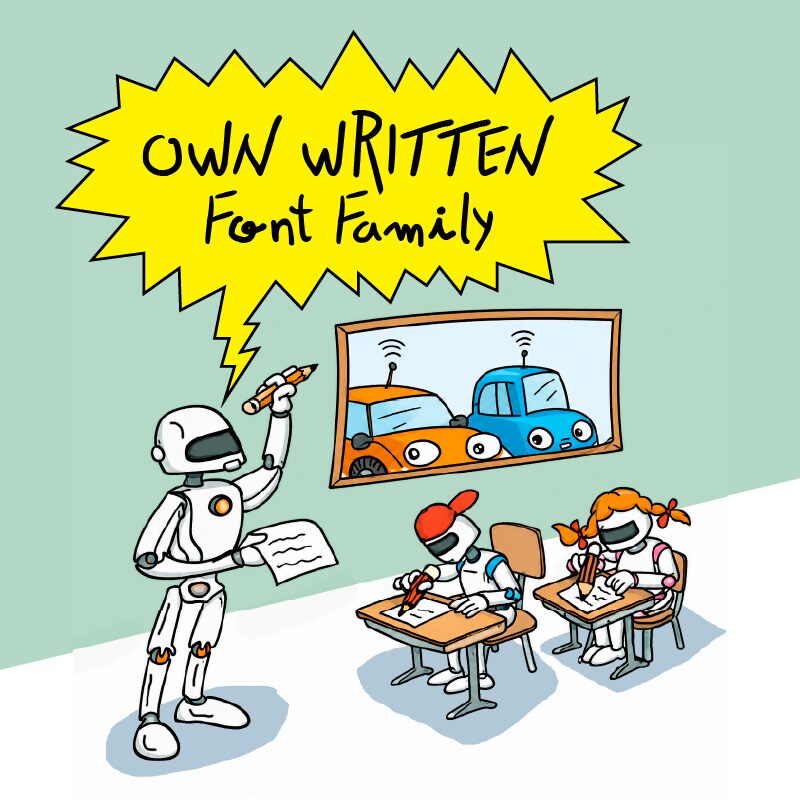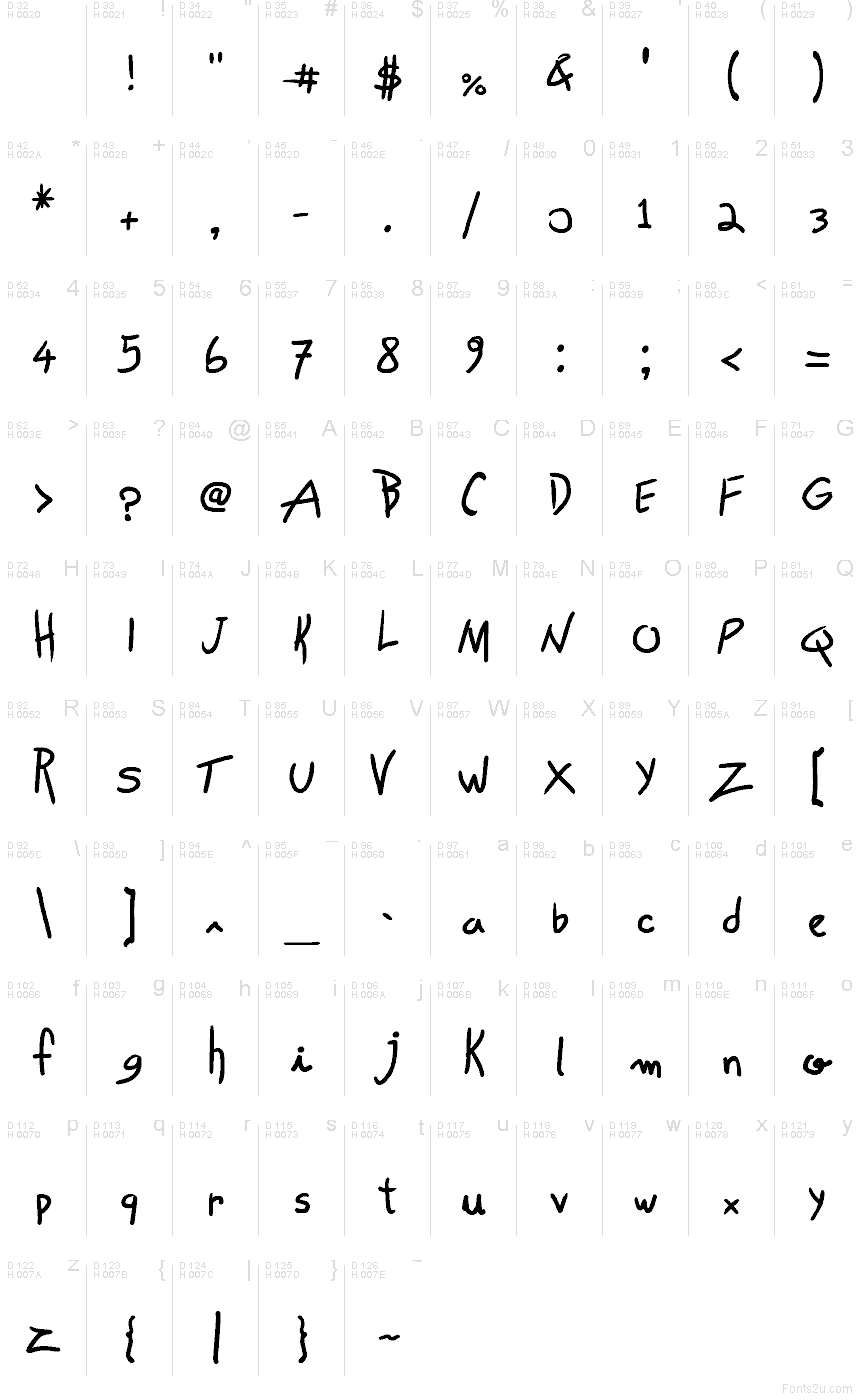
Own Written par Galdino Otten Fonts est une police manuscrite décontractée gratuite aux traits arrondis et au mouvement rapide et irrégulier d'une écriture au feutre. Ses liaisons souples et l'épaisseur changeante de ses traits confèrent à l'écriture un caractère personnel.
Les designers créant des projets conviviaux pour les familles ou les entreprises indépendantes peuvent l'utiliser pour des emballages pour enfants, l'identité visuelle de cafés et des affiches d'événements communautaires. Ses courbes douces conviennent aux produits dérivés ornés de mascottes dessinées à la main ou de simples gribouillages, où les lettres peuvent s'intégrer à l'illustration plutôt que de faire office d'étiquette formelle. Sa forme informelle se révèle particulièrement convaincante pour les thèmes culinaires ludiques, les activités manuelles et les événements musicaux détendus.